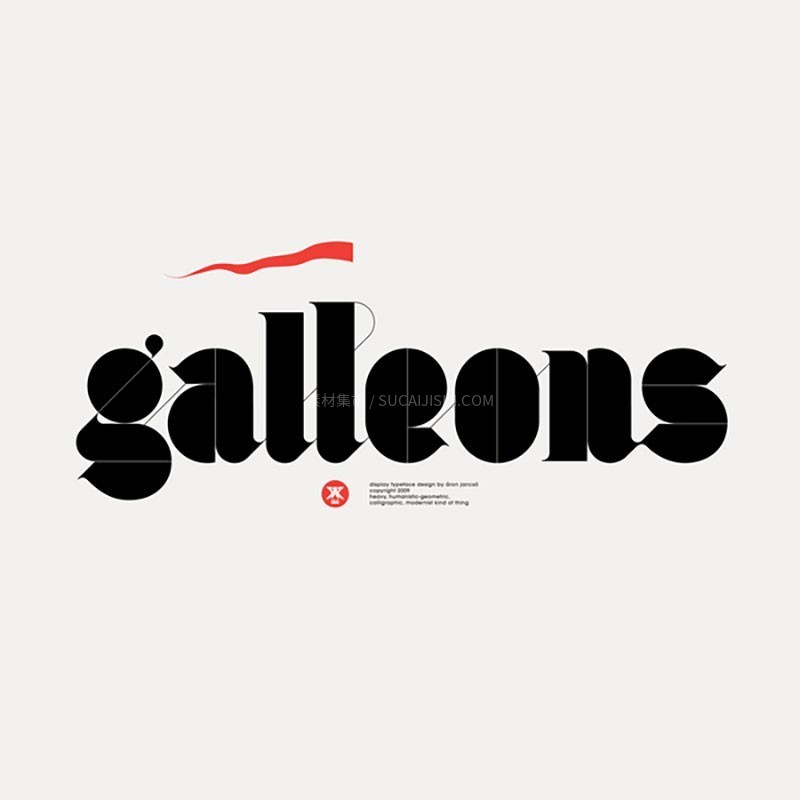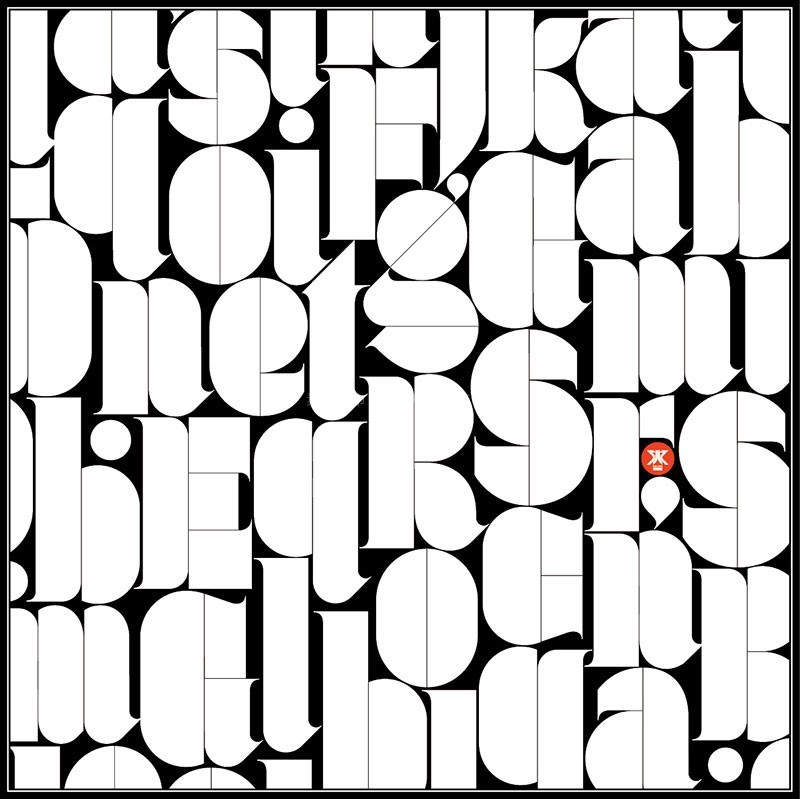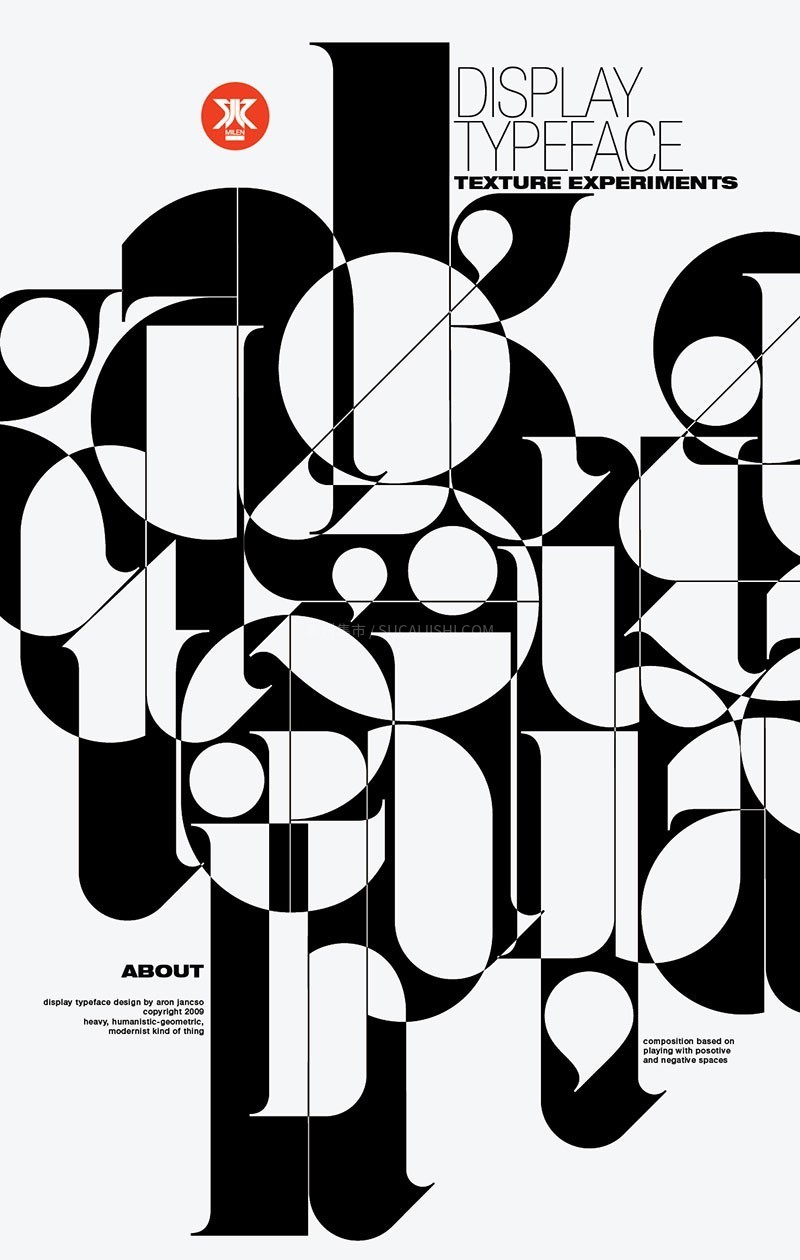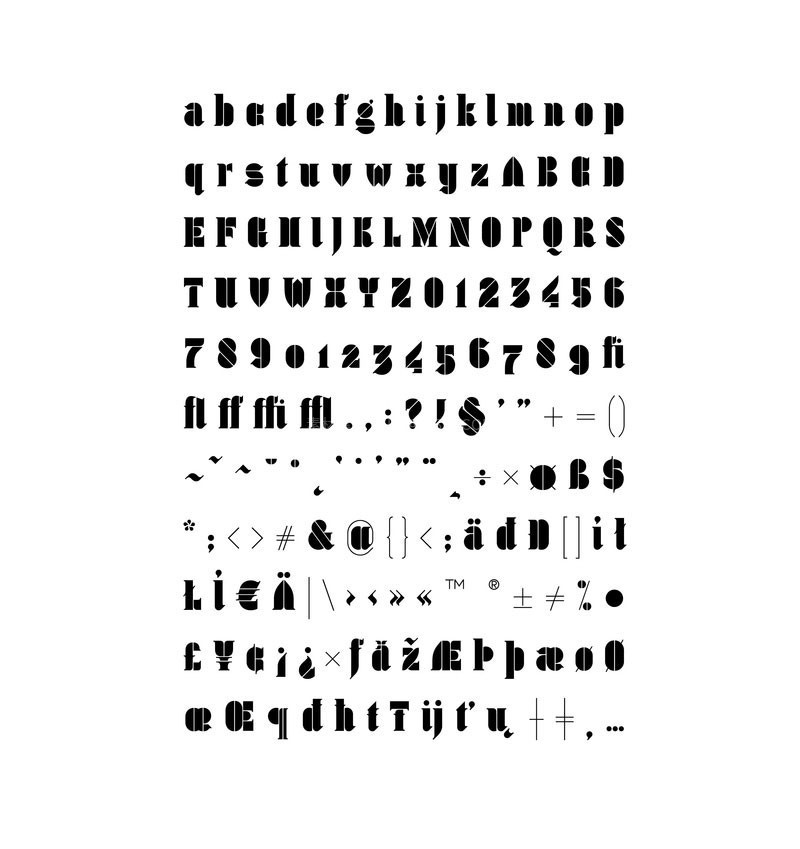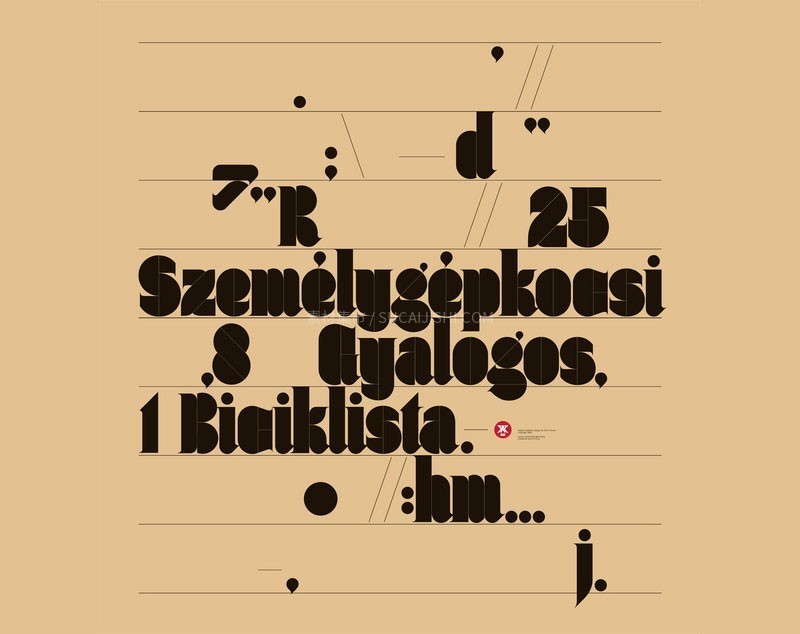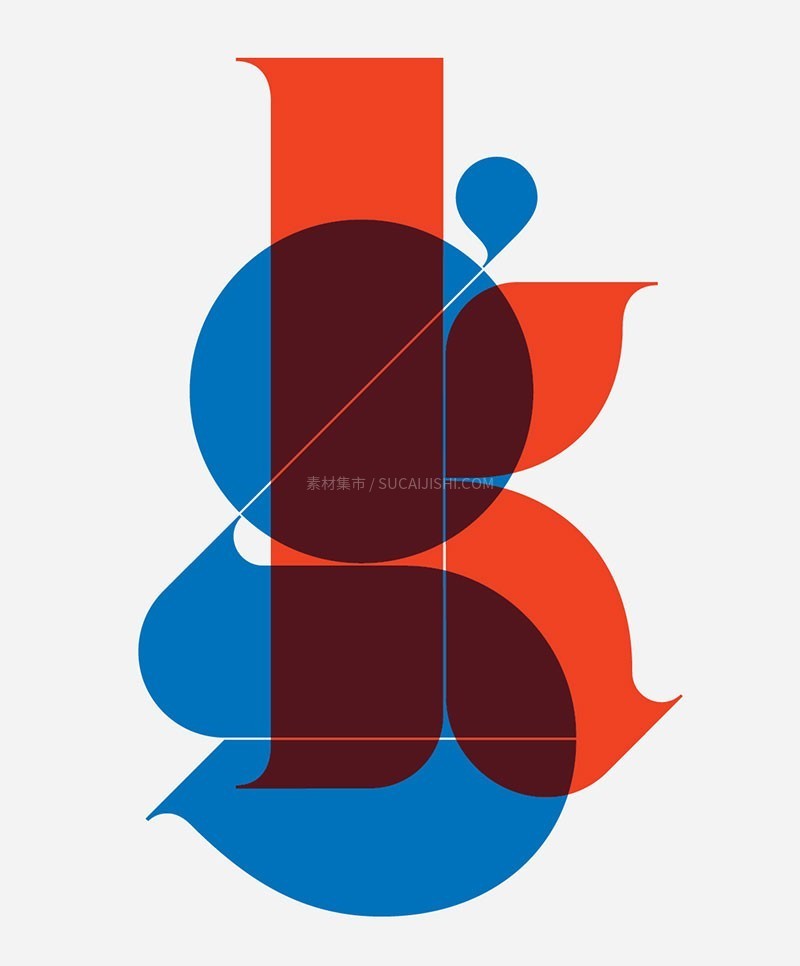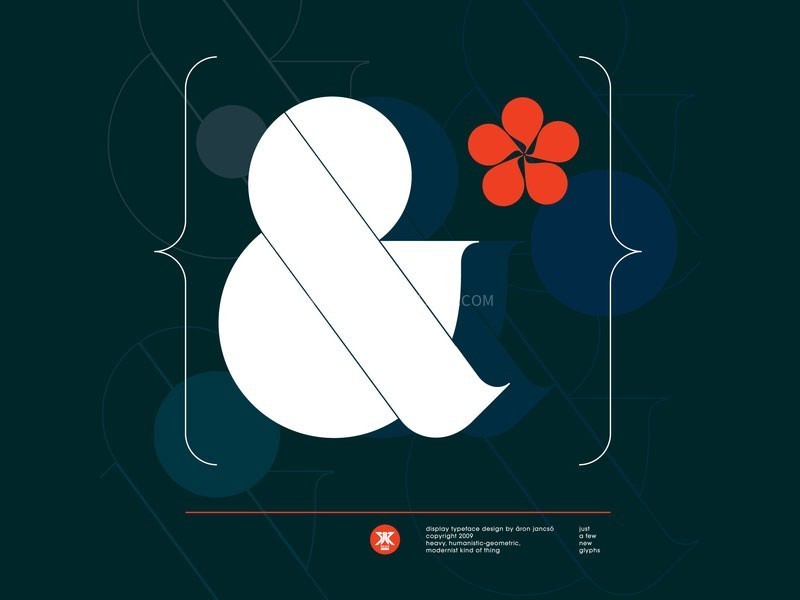
Ogaki超粗体英文海报标题字体
这是一款极具实验性的展示字体,线条大胆且充满张力,既展现了精美绝伦的艺术细节,又自带一种低调的奢华感。 该系列包含 Poster(海报体) 与 Text(文本体) 两种核心字重,并均配有对应的 Outline(轮廓版)。无论是冲击力十足的大字标题,还是细腻的文本排版,Ogaki 都能轻松驾驭,让你的文字设计脱颖而出。